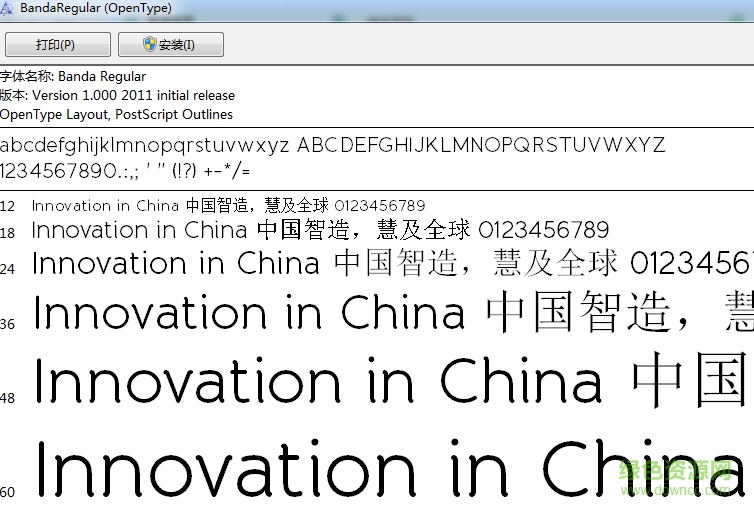
Banda字體是英文字體庫(kù)中的個(gè)性字體,字體線(xiàn)條非常纖細(xì),個(gè)性分明,讓用戶(hù)能夠一眼記住它,喜歡的朋友就來(lái)綠色資源網(wǎng)下載使用吧!
Banda字體是一款個(gè)性英文字體,字體非常適合用于平面設(shè)計(jì)行業(yè),有需要的朋友就趕快來(lái)綠色資源網(wǎng)下載吧!